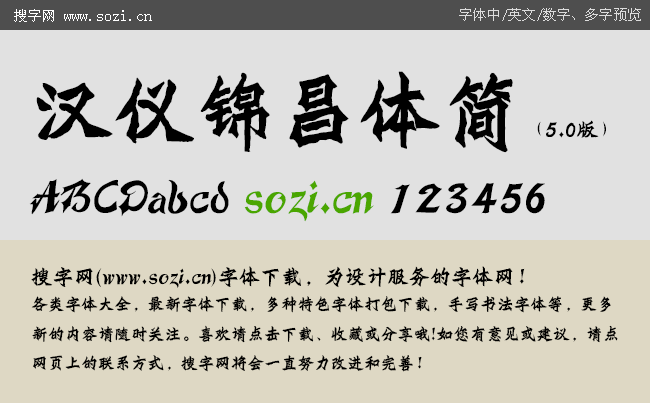
漢儀錦昌體簡5.0版
搜字網(wǎng)提供一款漢儀錦昌體簡中文書法字體下載,漢儀錦昌體簡是一款手寫風格的中文藝術(shù)字體,方筆行運筆畫寬坦,頓挫波折,棱角分明,有較好的統(tǒng)一性與視覺沖擊力?梢詰糜趶V告設計、包裝印刷、產(chǎn)品設計、海報設計等方面,有喜歡的朋友可免費下載收藏。